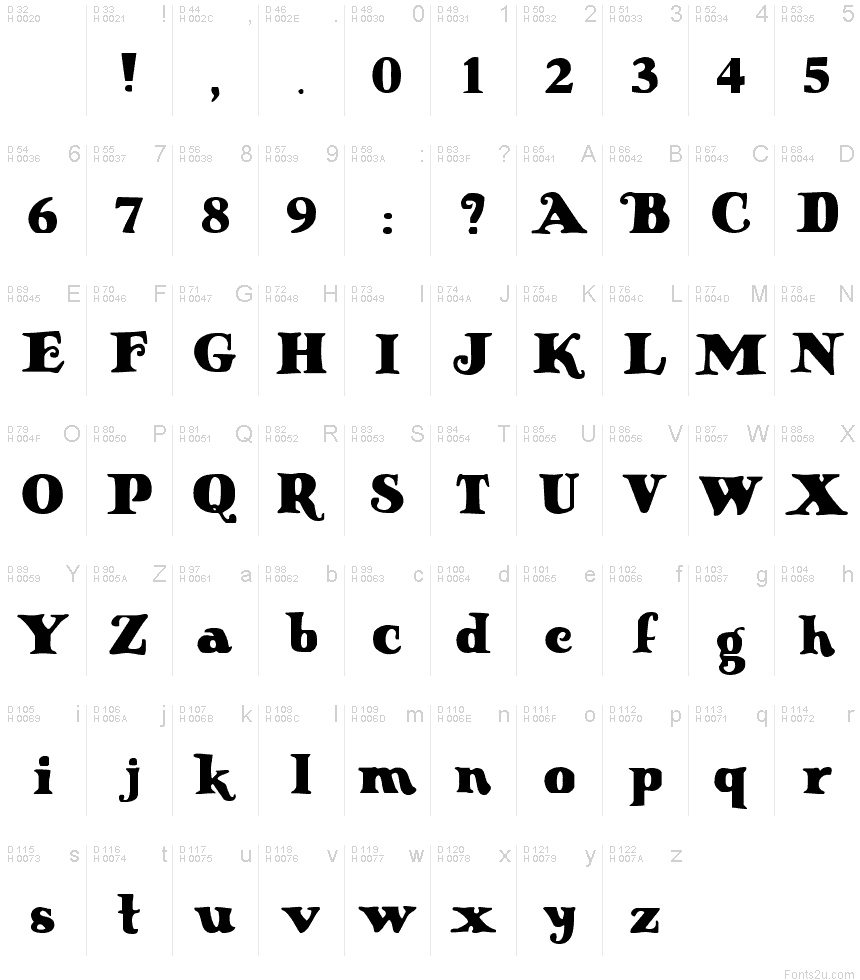
Knuffig od Anke Art to darmowy, retro font typu display, który zachwyca miękkim, „ręcznie wycinanym” charakterem. Litery pęcznieją i zwężają się niczym kleksy tuszu odciśnięte na papierze, nadając każdemu słowu zabawny, lekko chwiejny, ale wciąż czytelny rytm. Ten font emanuje przytulnym, baśniowym urokiem – łącząc klimat funky plakatów z lat 70. z ludowym rękodziełem – dzięki czemu tekst staje się ciepły, gościnny i odrobinę figlarny.
Knuffig błyskawicznie dodaje charakteru nagłówkom na plakatach eventowych, okładkach książek dla dzieci, opakowaniach handmade, menu kawiarnianym, identyfikacjach wizualnych produktów rzemieślniczych czy grafikach do mediów społecznościowych. Ten darmowy font najlepiej prezentuje się w dużych rozmiarach, gdzie jego skoczne krzywizny i wyraziste kształty mogą w pełni zaistnieć. Zestaw go z prostym krojem bezszeryfowym w tekście głównym i pozwól, by Knuffig przejął rolę w przyjaznych, dużych hasłach, które mają przyciągać wzrok.